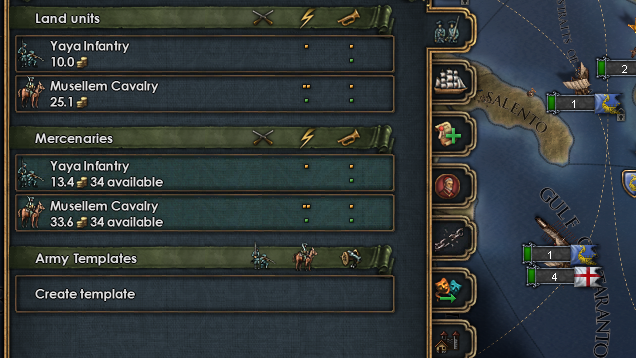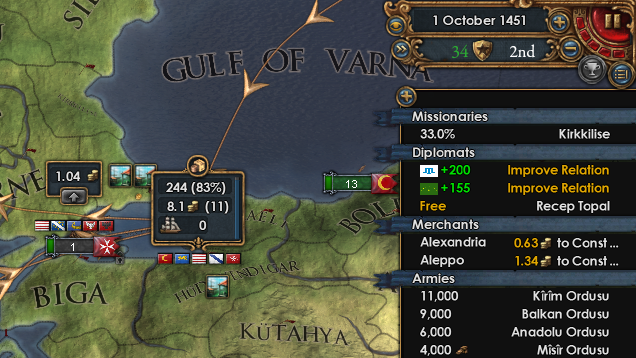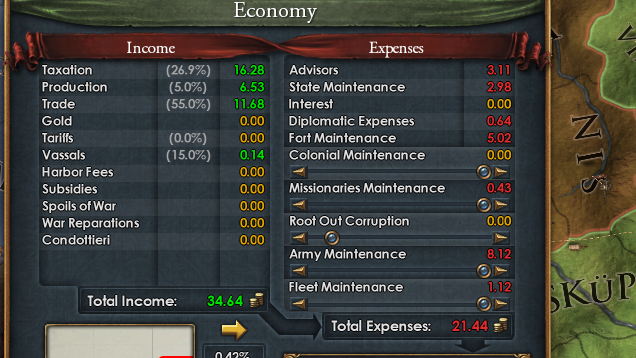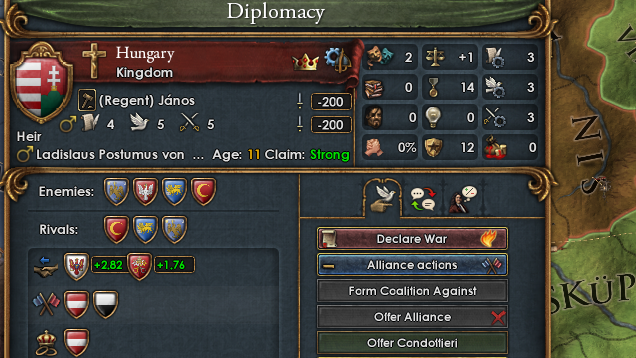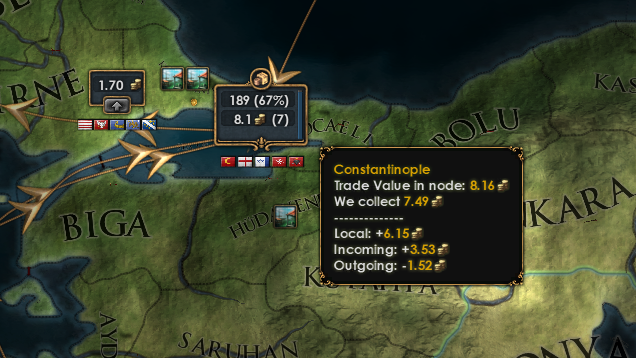
[MOD EU4] Stellaris UI Font
Небольшая модификация для игры Europa Universalis IV, заменяющая стандартный текстовый шрифт
Stellaris UI Font — это небольшая модификация для игры Europa Universalis IV, заменяющая стандартный текстовый шрифт похожим на тот, что используется в проекте Stellaris. Автор проделал немалую работу, вручную перерисовав все текстовые символы в игре, и не смотря на, казалось бы, незначительную роль привносимых изменений, некоторым игрокам они придутся по душе, :006: так как текста во всех играх от компании Paradox очень много, и поэтому крайне важно комфортно распределять зрительную нагрузку. :083:
Ниже вы сможете прочитать несколько важных сведений о работе Stellaris UI Font:
• Адаптированный шрифт из проекта Stellaris.